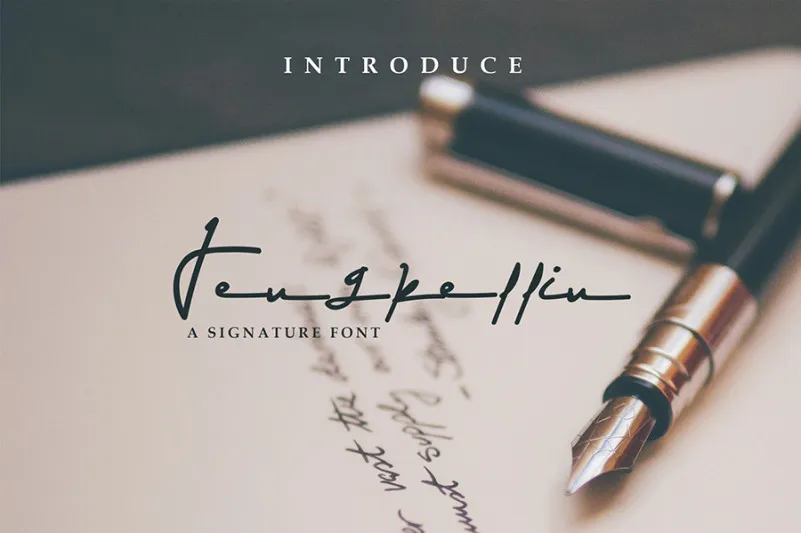
Jengkellin Signature Font – Download Grátis
A Jengkellin é uma fonte feita à mão, oferecendo uma aparência elegante e sofisticada que traz um toque moderno às suas criações. Desenvolvida por Sillii Willinn e compartilhada pela Graph2design, esta fonte está repleta de frescor original no tom da mão das letras, criando um estilo fashion simples. Os desenhos finais têm uma aparência que remete à personalidade encantadora da Turma da Mônica, com suas cores vibrantes e personagens únicos. Como resultado, Jengkellin é perfeito para aqueles projetos digitais variados, desde as citações até a embalagem de produtos em potencial ou promoção social, passando por cartas de casamento e assinaturas pessoais. O designer M.0Type nos oferece uma opção versátil que certamente tornará sua produção um pouco mais criativa e única.